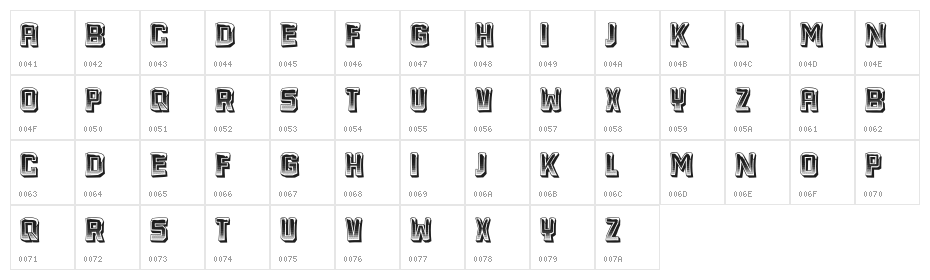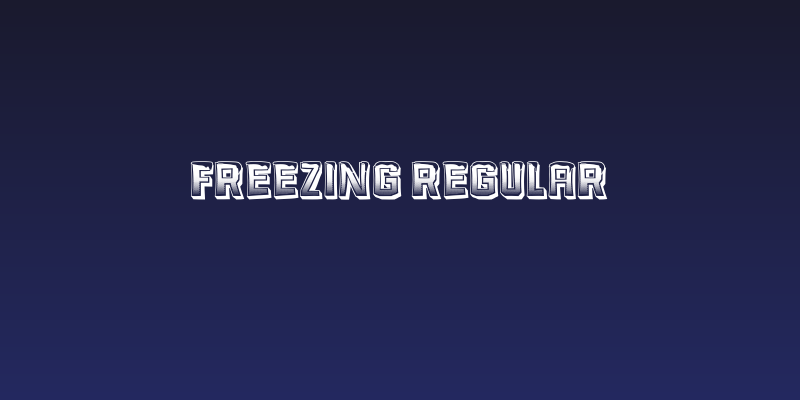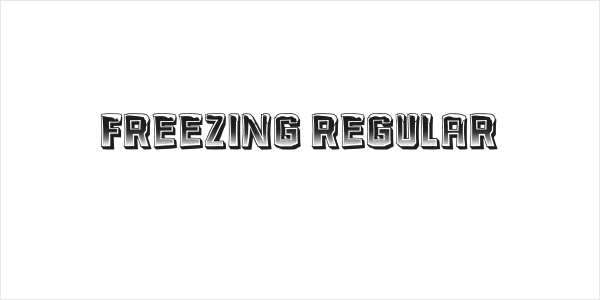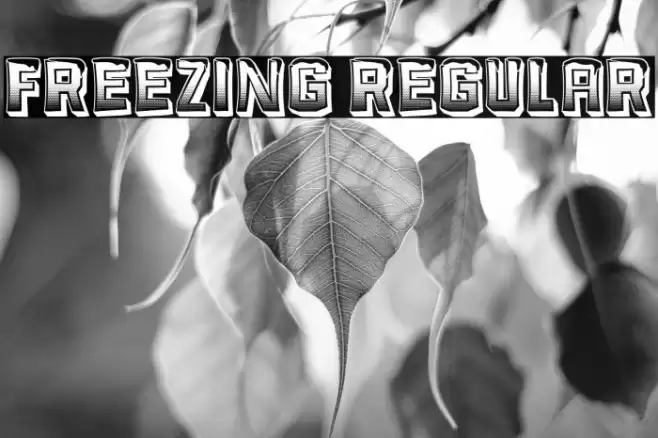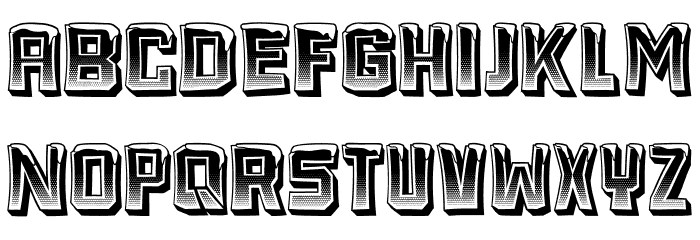
Freezing Regular Font
| 分类 | Cartoon |
| 整体风格 | Vintage |
| 推荐项目 | Ideal for retro-themed posters, comic book covers, video game titles, and any design requiring a bold, eye-catching typeface. |